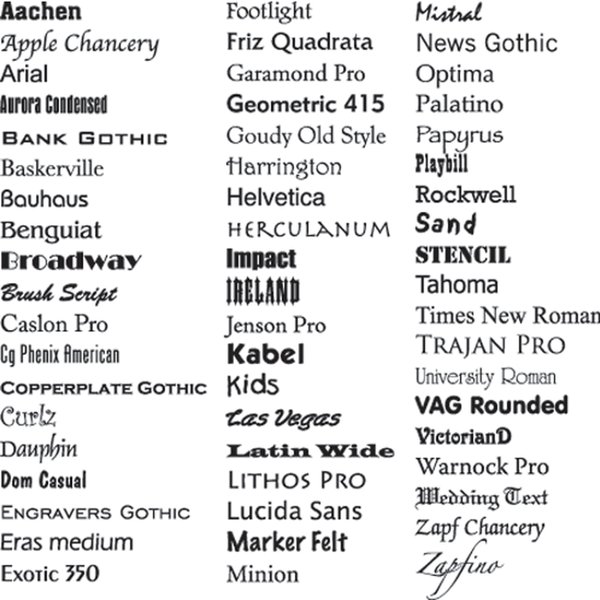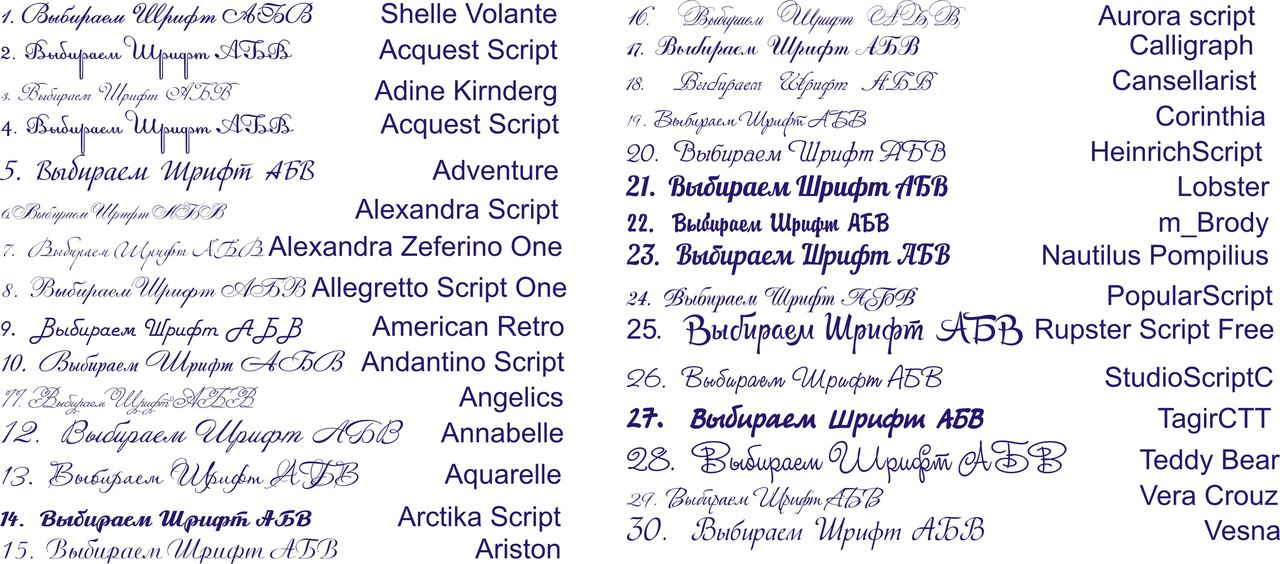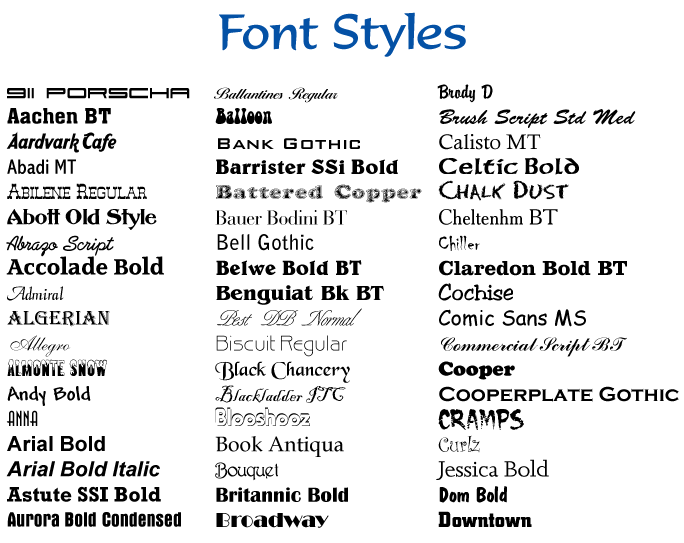
Примеры шрифтов с названиями: Образцы русифицированных шрифтов. Безопасные шрифты. Примеры русифицированных шрифтов.
Образцы русифицированных шрифтов. Безопасные шрифты. Примеры русифицированных шрифтов.
Браузер посетителя может отобразить только те шрифты, которые установлены в его операционной системе.
На этой странице приведен список русифицированных шрифтов, включённых в каждую версию Windows. Такие шрифты называют безопасными шрифтами для браузеров.
Распространенныерусифицированные шрифты для сайта (Стандартные шрифты Windows) | |
| Вид на странице | Название шрифта |
| Шрифт | — Arial |
| Шрифт | — Arial Cyr |
| Шрифт | — Arial Black |
| Шрифт | — Book antiqua |
| Шрифт | — Bookman old style |
| Шрифт | — Calibri |
| Шрифт | — Cambria |
| Шрифт | — Candara |
| Шрифт | — Century |
| Шрифт | — Century gothic |
| Шрифт | — Comic Sans Ms |
| Шрифт | — Consolas |
| Шрифт | — Constantia |
| Шрифт | — Corbel |
| Шрифт | — Courier |
| Шрифт | — Courier New |
| Шрифт | — Courier, monospace |
| Шрифт | — Cursive |
| Шрифт | — Franklin Gothic |
| Шрифт | — Gabriola |
| Шрифт | — Garamond |
| Шрифт | — Georgia |
| Шрифт | — Helvetica |
| Шрифт | — Impact |
| Шрифт | — Lucida console |
| Шрифт | — Lucida Sans Unicode |
| Шрифт | — Mistral (Mistral) |
| Шрифт | — monospace |
| Шрифт | — Monotype Corsiva |
| Шрифт | — MS Sans Serif |
| Шрифт | — MS Serif |
| Шрифт | — Palatino Linotype |
| Шрифт | — Sans-serif |
| Шрифт | — Segoe print |
| Шрифт | — Segoe script |
| Шрифт | — Sylfaen |
| Шрифт | — Tahoma |
| Шрифт | — Times New Roman |
| Шрифт | — Trebuchet ms |
| Шрифт | — Verdana |
Семейства шрифтов
После цвета шрифт — возможно, важнейшее свойство страницы. На этой странице я не буду демонстрировать никаких «трюков», но покажу ряд вариаций шрифтов, допустимых в CSS.
Поскольку не все шрифты доступны на всех компьютерах (существуют
тысячи шрифтов и большинство из них не бесплатны), CSS
предусматривает резервную систему. Первым вы указываете шрифт,
который хотели бы использовать. Затем следуют любые шрифты, которые
вы могли бы использовать, если первый указанный шрифт не доступен.
А закончить список вы должны типовым шрифтом, который
имеет 5 видов: serif, sans-serif, monospace,
cursive и fantasy.
Следующая таблица показывает примеры различных шрифтов (ваш браузер может не знать их все) и вы можете увидеть, что ваш браузер делает с каждым из пяти типовых шрифтов:
| ‘sans-serif’: обычные шрифты без засечек | ||
|---|---|---|
Arial, sans-serif | Съешь же ещё этих мягких французских булок да выпей чаю | |
Helvetica, sans-serif | Съешь же ещё этих мягких французских булок да выпей чаю | |
Verdana, sans-serif | Съешь же ещё этих мягких французских булок да выпей чаю | |
Trebuchet MS, sans-serif | Съешь же ещё этих мягких французских булок да выпей чаю | |
Gill Sans, sans-serif | Съешь же ещё этих мягких французских булок да выпей чаю | |
Noto Sans, sans-serif | Съешь же ещё этих мягких французских булок да выпей чаю | |
Avantgarde, TeX Gyre Adventor, URW Gothic L,
sans-serif | Съешь же ещё этих мягких французских булок да выпей чаю | |
Arial Narrow, sans-serif | Съешь же ещё этих мягких французских булок да выпей чаю | |
sans-serif | Съешь же ещё этих мягких французских булок да выпей чаю | |
| ‘serif’: обычные шрифты с засечками | ||
Times, Times New Roman, serif | Съешь же ещё этих мягких французских булок да выпей чаю | |
Georgia, serif | Съешь же ещё этих мягких французских булок да выпей чаю | |
Palatino, URW Palladio L, serif | Съешь же ещё этих мягких французских булок да выпей чаю | |
Bookman, URW Bookman L, serif | Съешь же ещё этих мягких французских булок да выпей чаю | |
New Century Schoolbook, TeX Gyre Schola, serif | Съешь же ещё этих мягких французских булок да выпей чаю | |
serif | Съешь же ещё этих мягких французских булок да выпей чаю | |
| ‘monospace’: шрифты фиксированной ширины | ||
Andale Mono, monospace | Съешь же ещё этих мягких французских булок да выпей чаю | |
Courier New, monospace | Съешь же ещё этих мягких французских булок да выпей чаю | |
Courier, monospace | Съешь же ещё этих мягких французских булок да выпей чаю | |
FreeMono, monospace | Съешь же ещё этих мягких французских булок да выпей чаю | |
Правильный шрифт для заголовков зависит не только от его формы, но и от того, как он используется и как наносится на бумагу. Хотя правильный выбор, безусловно, может улучшить сообщение, также необходимо следить за естественным течением страницы, наличием пустого пространства, иерархией шрифтов и тем, как они отличаются друг от друга.